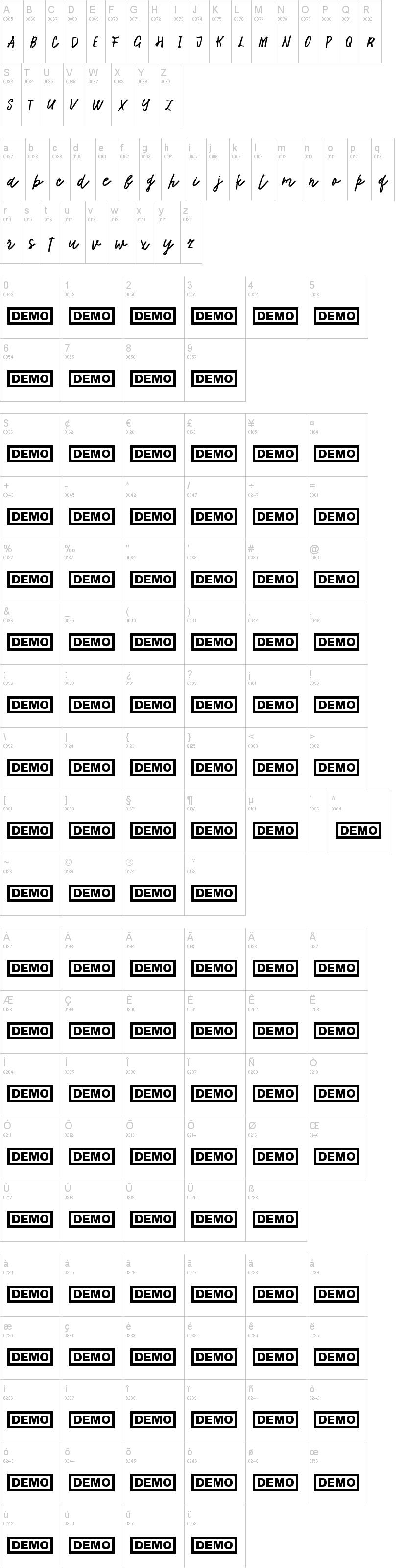
? Tadworth 字体是一款现代感十足的字体,它具有细腻的笔画和清晰的线条,适合用于当代设计中的文字和标题。它具有极具表现力的设计,可以提供鲜明的视觉效果,同时又能保持清晰的细节。Tadworth 字体的典型应用包括商业宣传、广告、品牌标识、网页设计等。内容介绍
Tadworth是一款非常不错的手写艺术字体,具有很好的视觉感,适合于文化类的宣传设计、商业类品牌的广告和产品包装设计以及个性化文字排版等较多场景。